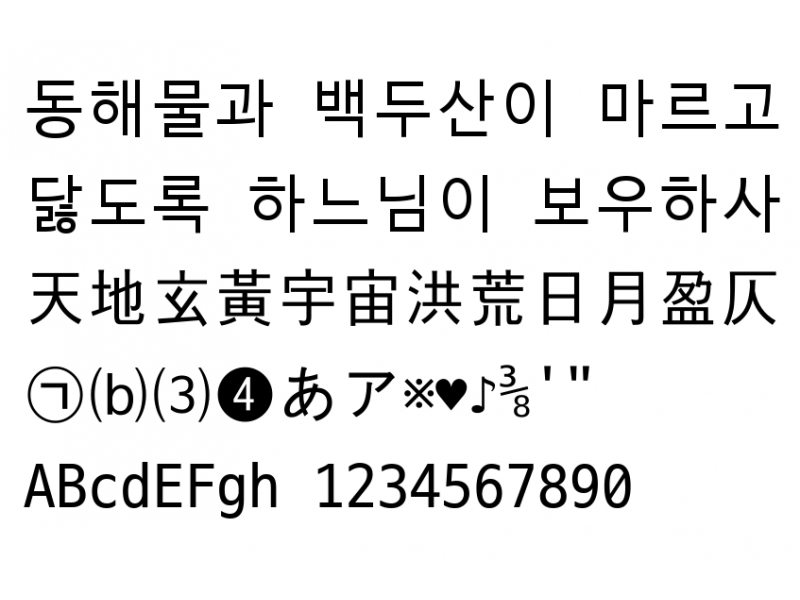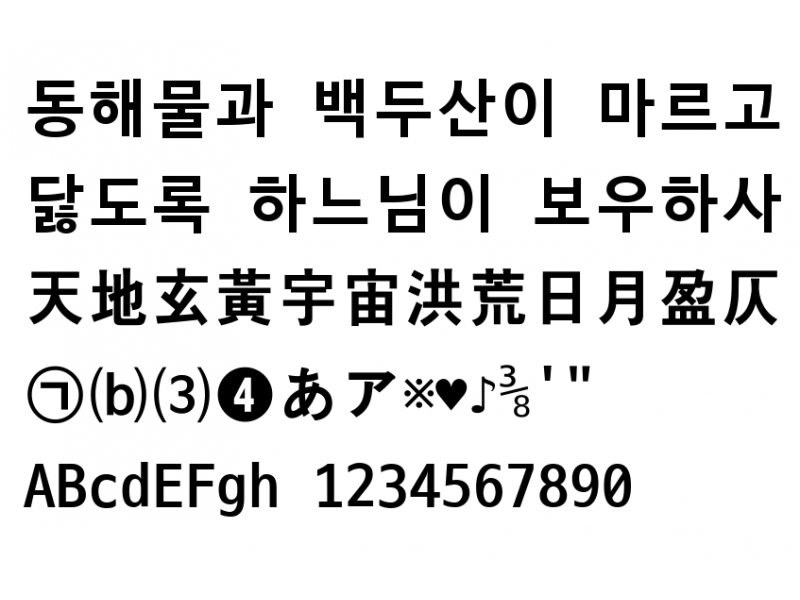
D2 Coding 글꼴은 나눔바른고딕을 바탕으로 개발자의 코딩을 위해 가독성 및 유사 문자간 변별력 뿐만 아니라 디자인적으로 한글과의 조화를 고려해 최적화시킨 글꼴이다. D2 Coding 글꼴은 코딩시 유사한 형태의 영문/숫자 뿐만 아니라 한글/특수문자 등에 대한 변별력과 가독성을 강화했다. 또한 고정폭 글꼴로 제작이 되어 어떤 개발환경에서도 자간과 행간을 유지하도록 디자인되어 있다.
한글, 영문자 및 확장자 332자에 대해 디자인이 되어 있으며 한자는 포함되어 있지 않다. (한자를 표시해야 할 경우 다른 글꼴로 대체) 제어 문자 31자가 포함되어 있다.